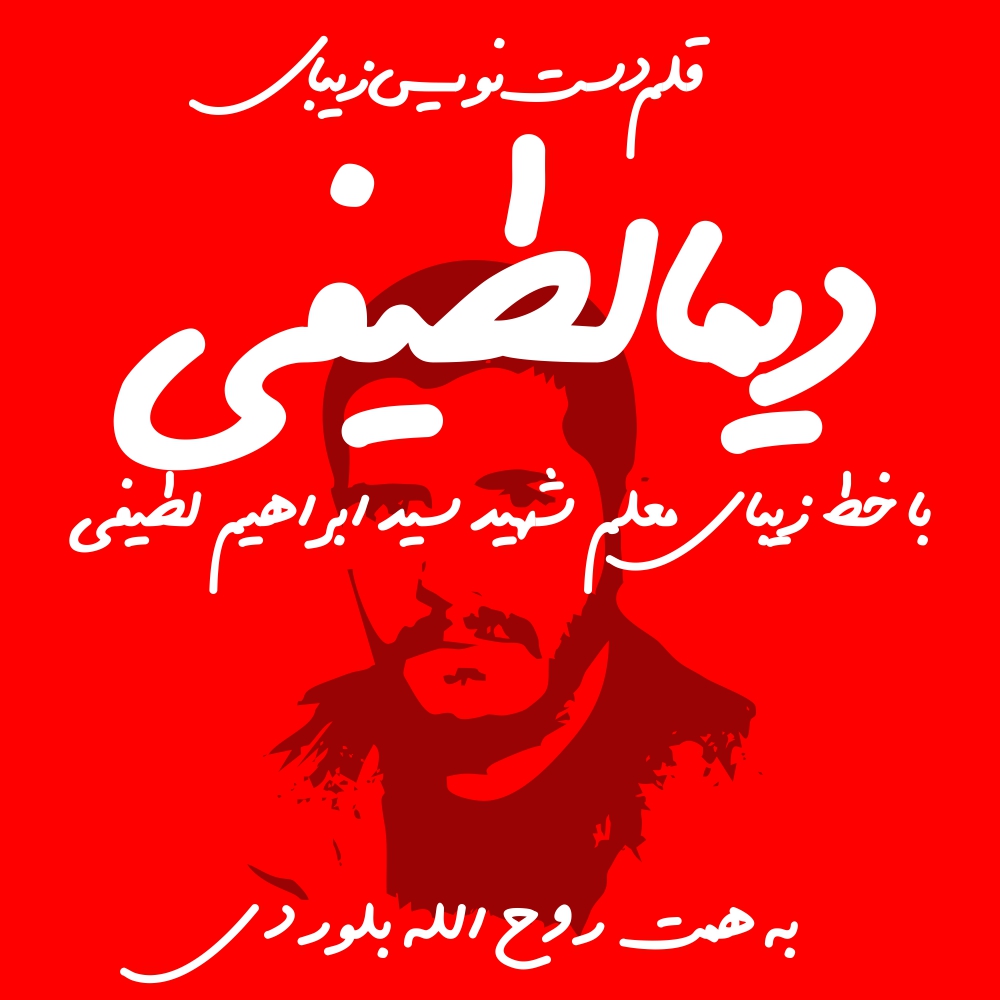
قلم دست نویس دیما لطیفی
فونت زیبای رایگان قلم دست نویس دیما لطیفی
این فونت براساس دست خط معلم شهید سید ابراهیم لطیفی طراحی شده است. شرط دانلود صلوات برای شادی روح این شهید عزیز و شهدای دفاع مقدس است.